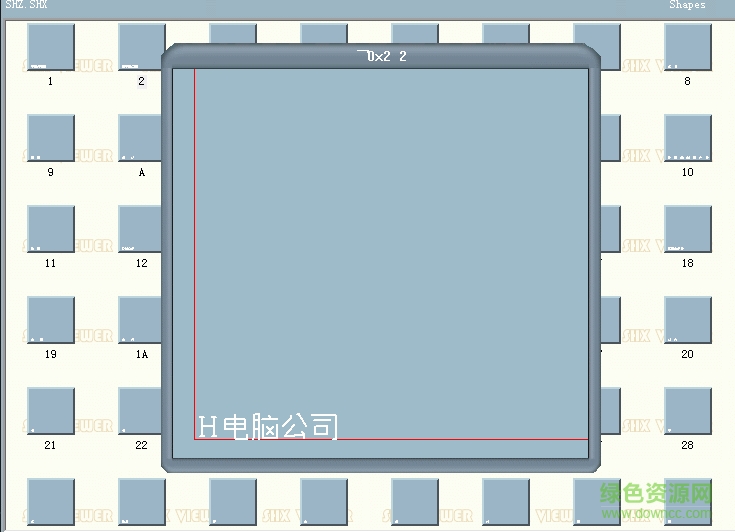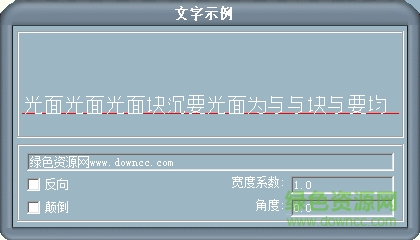
shz.shxcad字體中一款非常美觀的字體,在畫圖的時(shí)候可以直接進(jìn)行使用,支持輸入漢字、英文和阿拉伯?dāng)?shù)字,歡迎有需要的朋友到綠色資源網(wǎng)下載使用!
shz.shx字體是專為autocad軟件打造的一款字體文件,一般在設(shè)計(jì)圖紙的時(shí)候如果使用了shz.shx字體,那么,查看的時(shí)候電腦中也需要安裝一下shz.shx字體,否則將無法正常查看CAD圖紙,成功下載后將shz.shx字體放到CAD的字體目錄就可以使用了。